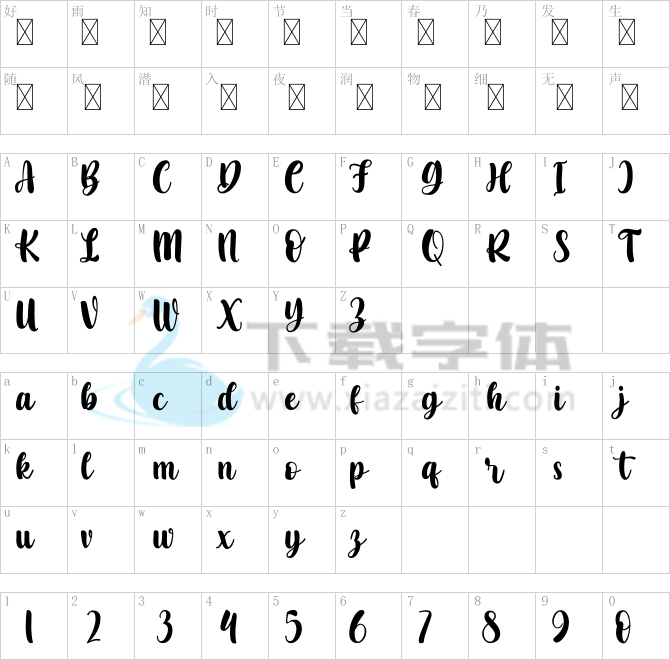
Arthur Taniya.otf字体下载,这款字体结构工整、笔画清晰,兼顾美观与易读性,适用于标题、正文、海报、包装、LOGO 等多种场景。字形优雅稳定,风格百搭耐看,适配日常排版与创意设计,让文字呈现更舒适、更具质感。Arthur Taniya.otf字体下载一笔一画,皆是细节,以均衡的比例、流畅的线条打造舒适视觉体验,字形端正大气,风格简约现代。无论是商业设计、品牌宣传还是日常排版,都能轻松驾驭,让文字更有格调与力量。Arthur Taniya.otf字体下载字体下载。